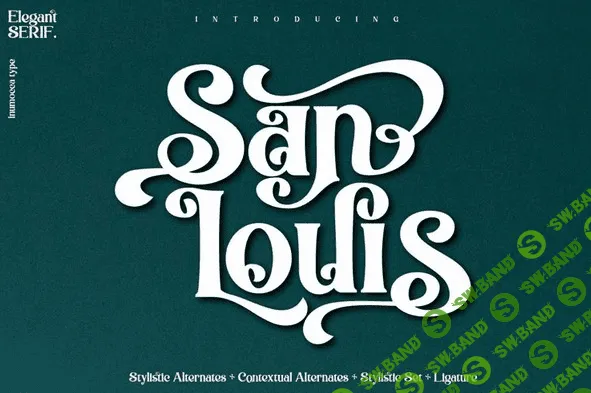
Название: San Louis Font
San Louis - это элегантный шрифт с засечками, современный, стильный и гламурный.
Потрясающий стилистический набор, красивая лигатура и уникальные контекстные альтернативы,
стилистические альтернативы. Действительно игривый шрифт для покрытия вашего проекта,
например, надписи, интерфейс веб-сайта, журнал, брендинг, плакат, свадебные приглашения,
Цитаты, надписи, логотипы и многое другое для вашего проекта.